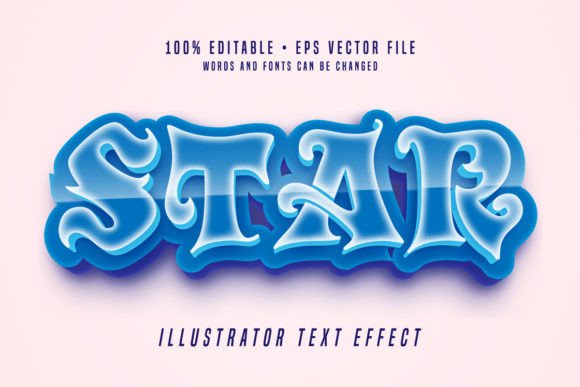
Star 3D Illustrator Text Effect Font
Если вы ищете высококачественные ресурсы, такие как Star 3D Illustrator Text Effect Font, этот премиум-пакет — фантастический выбор для ваших творческих проектов.